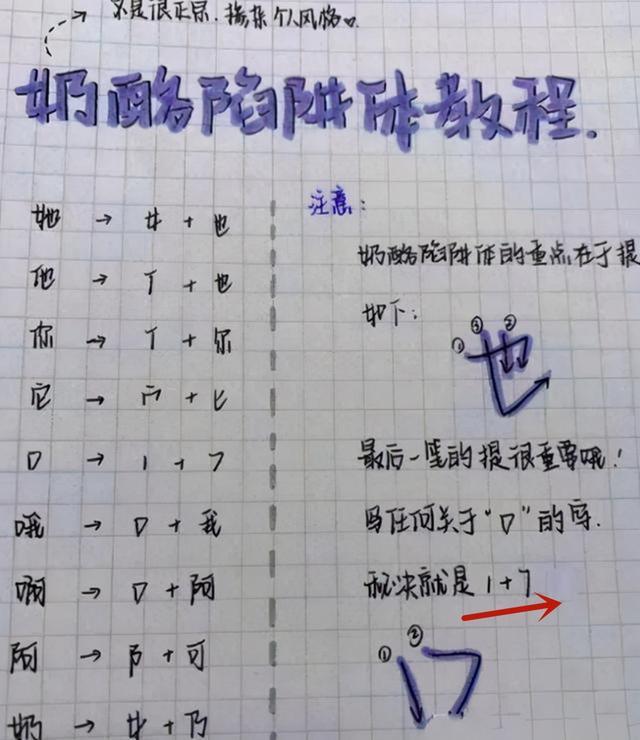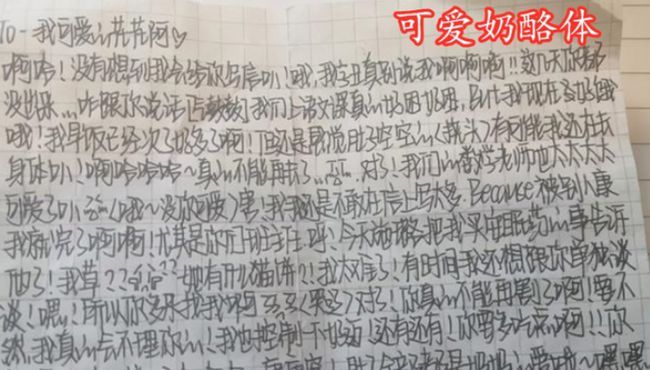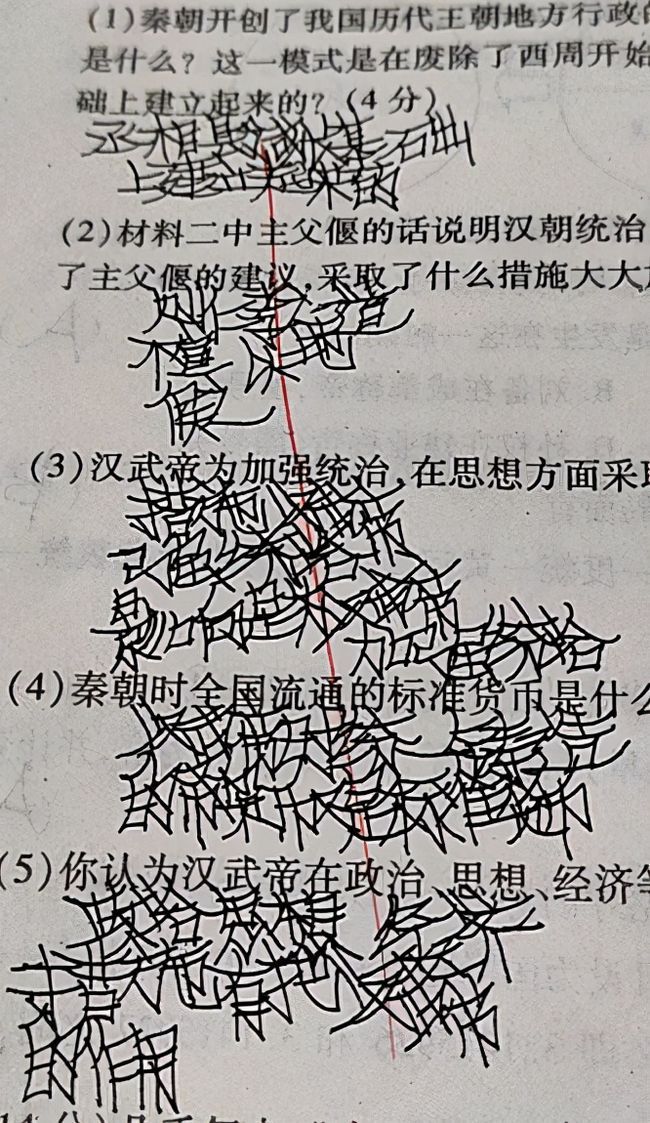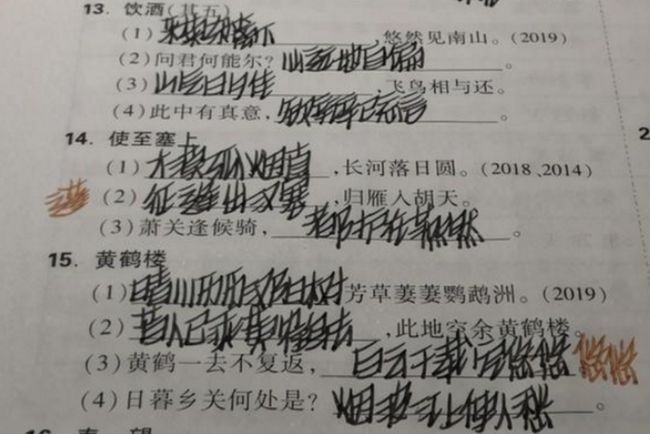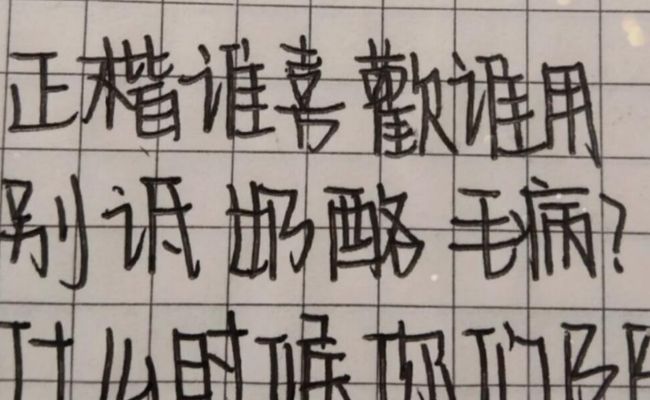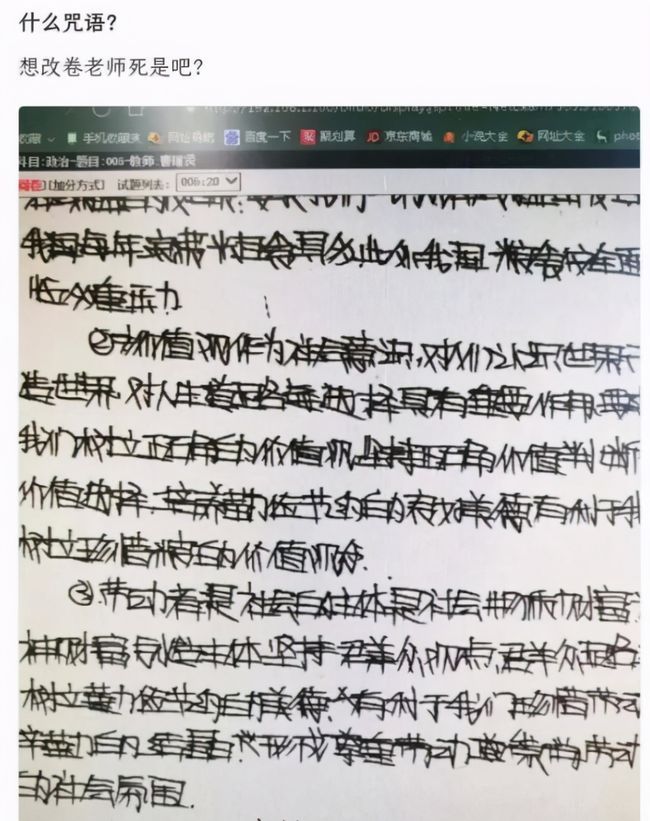
有一种“网红字体”奶酪体
字体书写不是一件一蹴而就的事情,需要长时间的日积月累,而学生时期的积累是最重要的,学生时代养成的书写习惯,影响着字体好不好看,而坏习惯一旦养成很难改变。
中国汉字历史悠久源远流长,有着上下五千年的历史文化,从古至今流传下来,形成五种固定的书写模式,分别是楷书、草书、隶书、篆书、行书,其中楷书是生生活中应用的最为广泛的。
楷书讲究横平竖直,字正方圆,给人一种笔锋很强劲,有一定文化底蕴的感觉。随着时代的变化,字体经过不断变迁也出现了很大的变化,曾经主流的楷书不被现在学生所喜欢的,取而代之的是一种网红字体。
有一种“网红字体”叫奶酪体
不知什么时候起,一种名为“奶酪体”的字体风靡网络,所谓奶酪体就是写的字像是刻在奶酪上一样,字体写出来很深很重,而奶酪体还有一个主要特点,就是“笔画缩略”,如下图所示,奶酪体的最后两笔都是连在一起写的,这也是奶酪体的一大精髓所在。
奶酪体写出来干净工整,还给人一种可可爱爱的二次元风格,一时间在高中女生之间风靡起来,很多女生开始在网上买专门练习奶酪体字帖,本可以也能写出可爱又工整的字体,没想到最后却练得不伦不类的。
练习奶酪体未成功的结果
• 工整但不好看
奶酪体固然看上去很工整,但是不符合中国汉字的书写逻辑,笔画不通畅,字体不正,下面字体就是一高中女生奶酪体没练明白的后果,但拿出一个字来看并不会觉得不好看,但是放在一起却说不出来的别扭,判卷老师看到这样的字体,尤其是在语文作文中成堆的这种字体出现时,看了想给0分。
• 写出鞋拔子字体
上述奶酪体没练明白写出来的字体虽然不好看,但是还能看清,而下面这个就有些让人不忍直视了,字横不不平竖不值,且都往一处倾斜,倾斜角度好似鞋拔子,大量书写出现给人一种“异域风情”的感觉,乍一眼不太像中国字的感觉。
总结:
上述两种出自高中女生之手的“奇葩字体”都是因为练奶酪体没练明白的后果,奶酪体固然好看,也很可爱,但不适用于正规的卷面书写。
尽管奶酪体练的很成功,写出来在考试中也不会有优势,反而老师对中国汉字有追求的老师,还会因此给你减分,毕竟从笔画上来看,奶酪体这种缩减的方式,确实是不正确的。
盲目练习“网红字体”会有哪些影响?
字写得不伦不类
字体书写也是要有悟性的,有的人天生对于充满艺术感的书法不感兴趣,但是也能正常写出工整的楷书,一旦这种人却特意练习奶酪体,很是一时间就练成功,到最后写出来的字不伦不类,让人结束无能,如同上面两种字体,老师看了头皮发麻。
练很容易,想纠正却很难
奶酪体毕竟是一种网红字体,并非主流汉字书法字体,很多专业教育人士是不能接受的,就比如一些判卷老师,看到这样的字体会减分。
而奶酪体或其他网红字体,鲸落体或者是柚圆体很好练成,但要改就很难了,当你意识到这种字体会成为你考高分路上的绊脚石,再想去改正需要花费巨大的人力和时间。
字体成为考试的一大劣势
上面我们也说了,奶酪体或其他网红字体,登不上大雅之堂,太过于小众了,一些判卷老师并不认这种字体,非但不觉得好看,还会觉得是书写错误,所以在中考高考中,老师遇到这种字体可能会减2-3分,成为考试中的一大劣势。
对于正在练奶酪体的学生想说
在网络爆炸时代下,网络上形形色色的消息很多,作为新兴人时代的领路人,应该有判断是非的能力,不要盲目去跟风某种事物,否则最后受伤害的就是你自己。
这种风靡全网的奶酪体就是网络时代下的产物,有人用荧光笔在宣纸上写出来又深又重的奶酪体,学生刷到后感觉很有仪式感很好看,然后开始跟风练习,殊不知这种字体只适用于视频拍摄,不适合正常的书写答题。
中国汉字有五千年前的历史,流传出来的五种字体书写都是文化的沉淀,不是这种网红字体可比的,所以说笔者在这里劝诫中小学生不要跟风去练习奶酪体、鲸落体、柚圆体这些网红字体,跟着老师学好楷书书写才是正道。